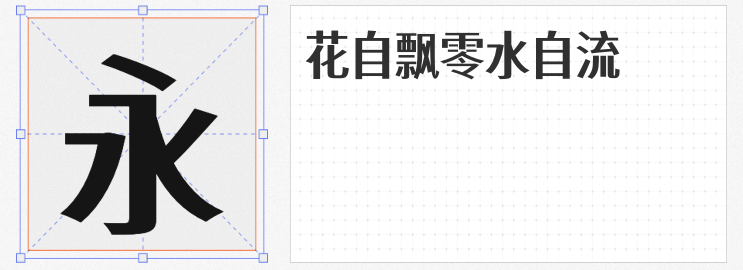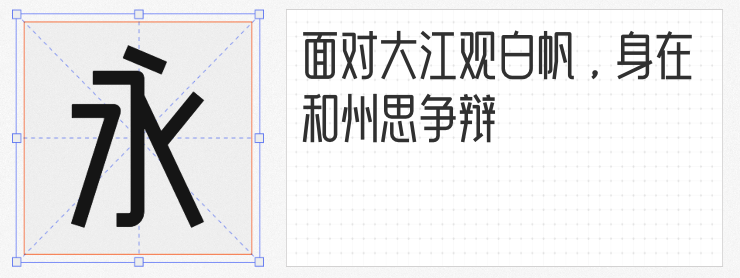
在海报设计的视觉竞技场中,字体的选择往往决定着信息的穿透力与风格的独特性。以下四款免费商用字体,以创意设计打破常规,既能满足商业需求,又能为作品注入鲜明个性。
1. 寒蝉有机体 Medium
基于思源黑体的“逆反差”革新之作,通过粗细笔画的戏剧性对比,打破传统黑体的平衡感。横画纤细如发丝,竖画粗壮似钢筋,这种矛盾美学赋予文字动态的张力,仿佛从二维平面中生长出的有机生命体。适合科技、艺术类海报,能瞬间抓住观众视线,传递前卫与实验精神。
以“极细”为核心理念的轻盈字体,重心上移的设计让文字仿佛悬浮于空中。笔画细若游丝却结构稳健,留白处暗藏呼吸感,如同水墨画中的飞白。这款字体尤其适合女性向、文创类海报,其空灵气质能营造出高级感与疏离感并存的视觉氛围。
3. 庞门正道细线体
以“方正匀称”为设计哲学,接近正方形的字框与90%的字面占比,构建出稳如磐石的视觉基础。中宫舒展的笔画布局,让文字在密集排版时依然保持清晰可读性。这款字体是信息类海报的利器,无论是促销活动还是产品说明,都能以理性美感传递核心内容。
4. 淘宝买菜营销体
AI技术赋能的智能字体,通过7套质感图片的智能生成,让每个字符都拥有独特的纹理与生命力。6974个汉字的全覆盖支持,配合默认优化的字距设置,既保证视觉多样性又提升设计效率。这款字体专为营销场景而生,在电商海报、活动宣传中能快速营造氛围,助力品牌信息高效触达。
这四款免费商用字体,以差异化设计满足多元场景需求,让设计师在无需成本压力的前提下,也能探索字体美学的无限可能。